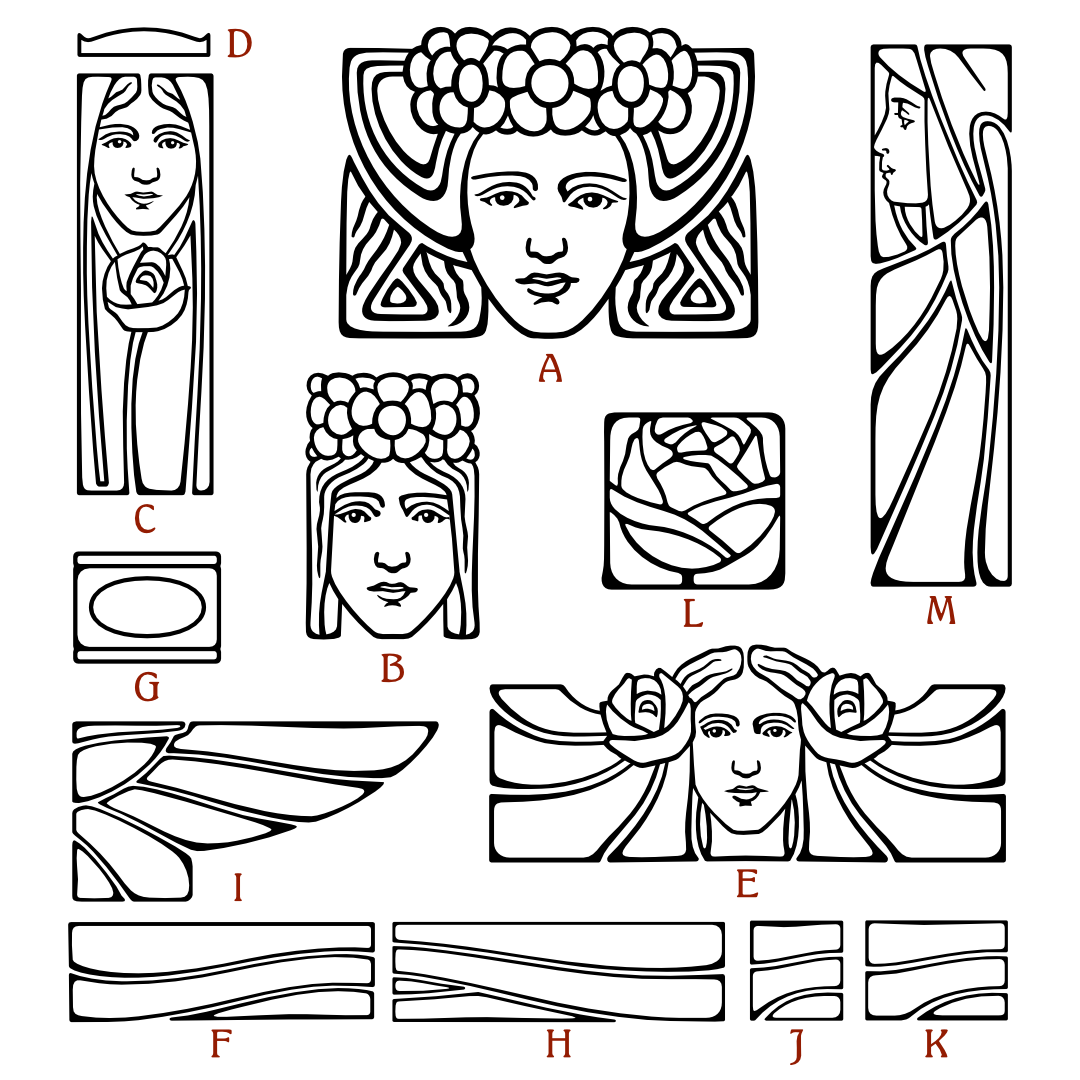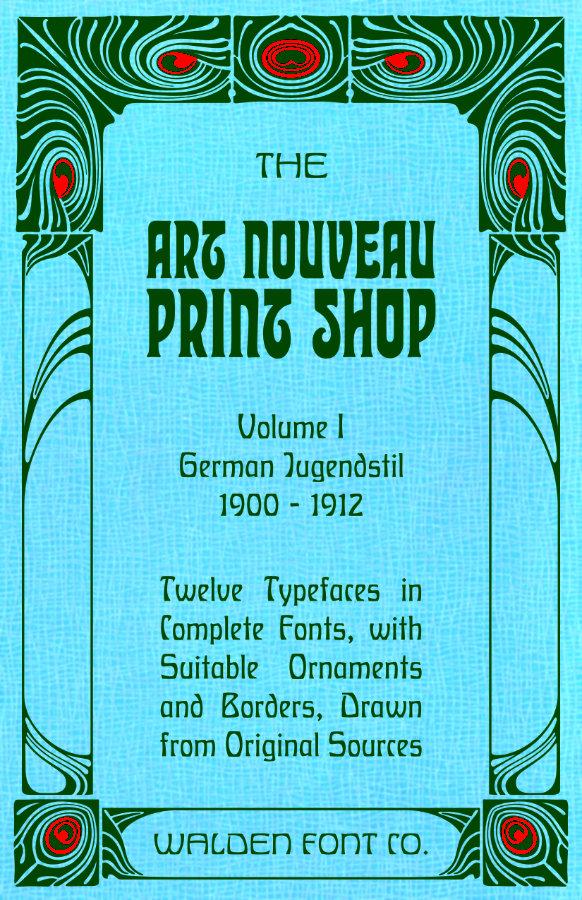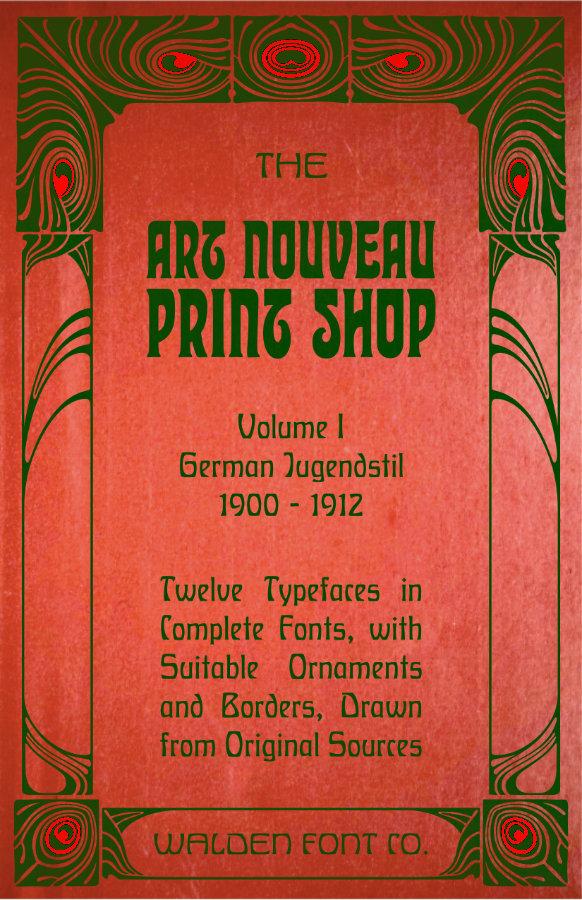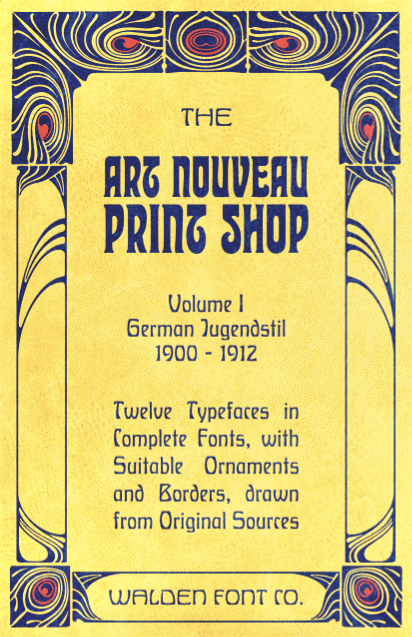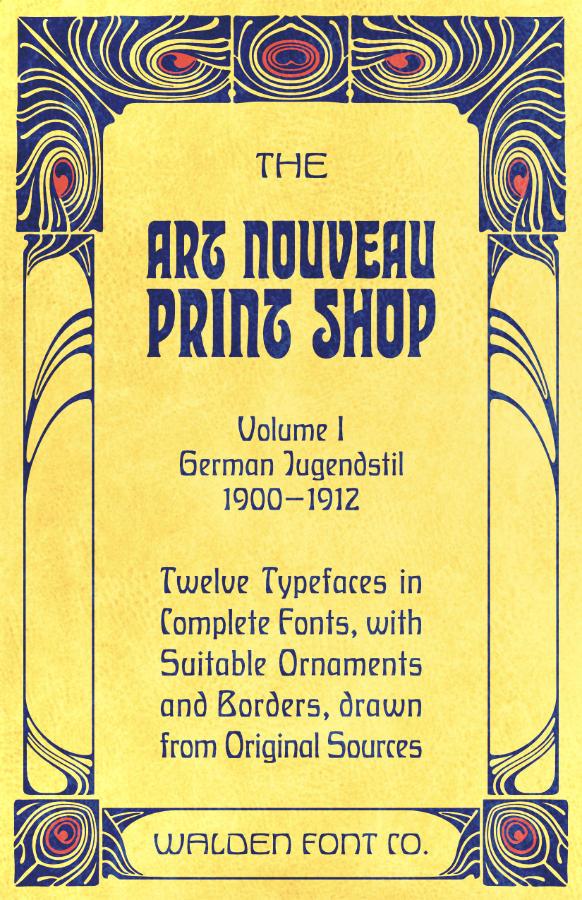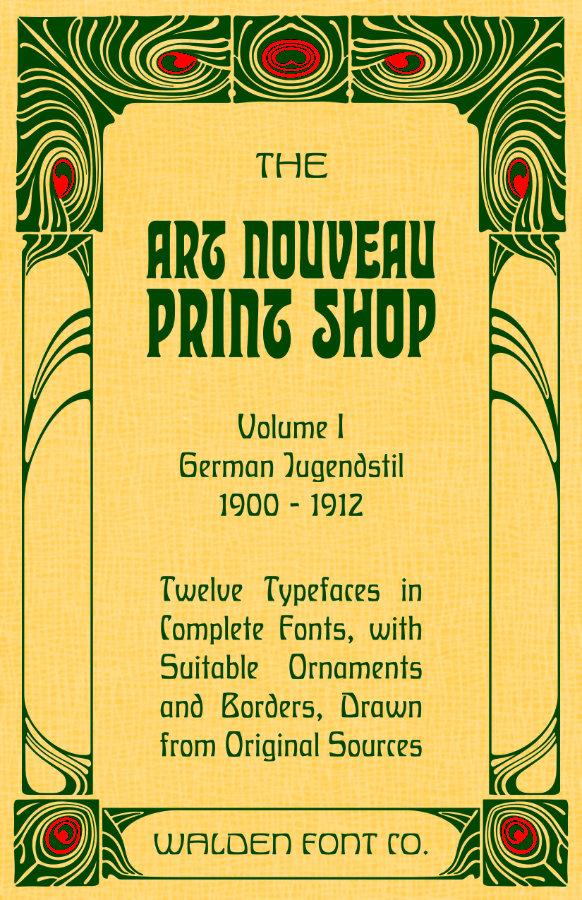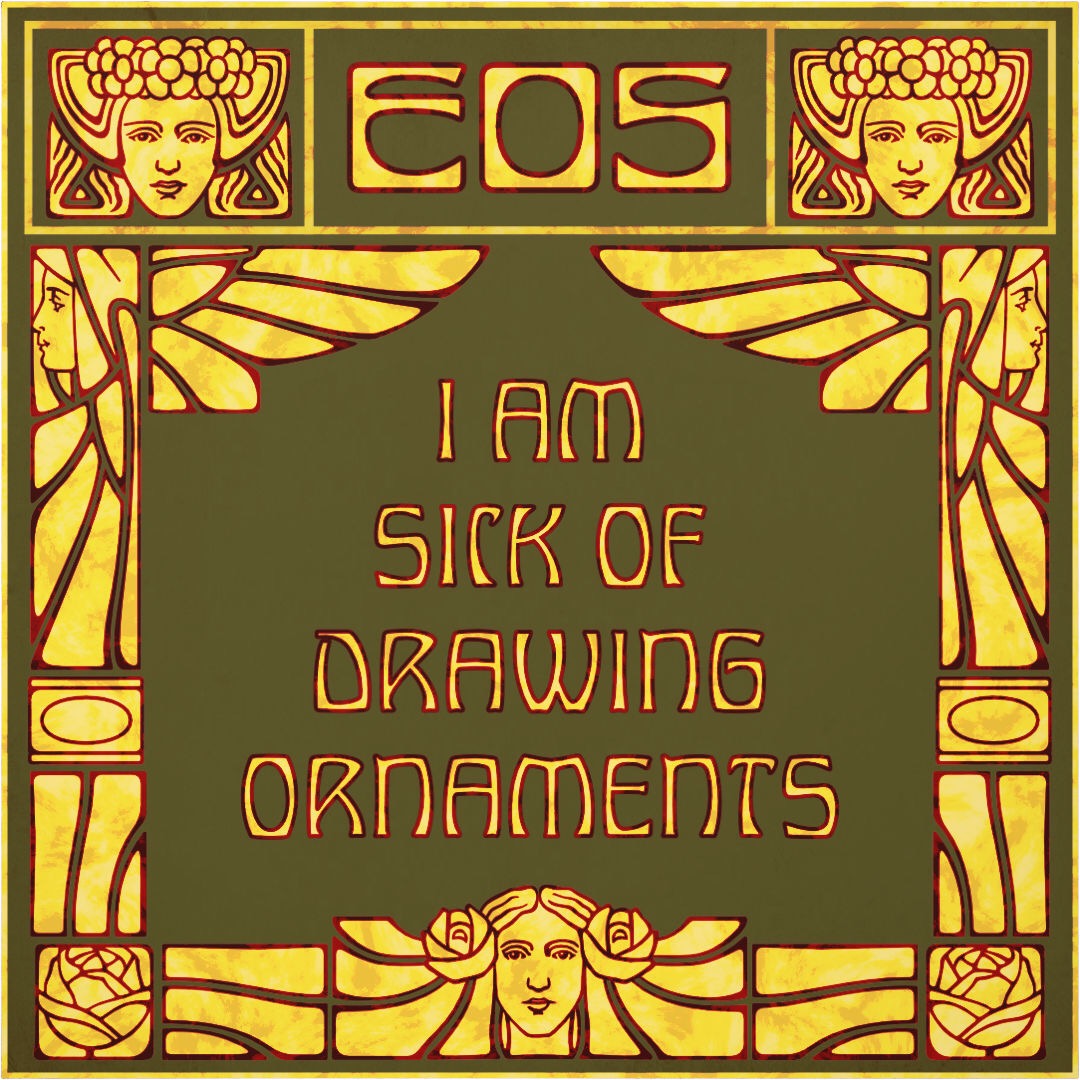
Jugendstil, Bordüren & Zierat
Gestern Abend war es schon spät, und zu mehr als einen Witz zu machen hatte ich keine Energie. In der Tat war das Bild ein erster Versuch an einem Titelblatt. Das brauche ich für meinen Website, aber auch, weil ich zu jedem Design Kit ein kleines Büchlein gestalte, in dem die Schriften erklärt werden, und das Anweisungen zu etwaigen OpenType features enthält, sowie verschiedene Anwendungen der Schriften.
Leider zeigt sich da oft, daß ich weder Künstler noch Grafischer Gestalter bin. Fehlschläge gehen mir viel leichter von der Hand als Erfolge...
Das angestrebte Titelblatt muß die folgenden Bedingungen erfüllen:
1. Sinn und Zweck müssen klar erkennbar sein, es muß also Art Nouveau/Jugendstil auf einen Blick vermitteln. (Das es sich um Schriften handelt, ist durch den Zusammenhang mit meiner Website gegeben)
2. Es verwendet nur Elemente aus dem Design Kit
3. Es muß grafisch ansprechend sein, und das Auge anziehen.
Mein erster Versuch erfüllt meiner Meinung nach vielleicht Punkt 1. und 2., aber keinesfalls 3. Zu fad, zu öd, auf Distanz nicht lesbar.
Hier habe ich mal mit verschiedenen Hintergründen gespielt:
Von den Farben her finde ich das unterste am ansprechendsten, wenn ich auch das Rot etwas kräftig finde. Aber das Gelb-Grüne sieht schon so schön alt aus 🙂
Allgemein verbinde ich irgendwie mit Jugendstil immer etwas, nun ja, plüschiges (vielleicht ist verspielt besser, jedenfalls für mein Gefühl jede Menge überflüssiges Gedönse), leicht "verdrecktes" (abgegriffen, staubig).
Das trifft vielleicht mehr auf den vorhergehenden Stil zu, der bei uns "Victorian", in Deutschland (glaube ich) "Wilhelminisch" bezeichnet wird. Der Jugendstil in seiner reinen Form (der damals ja nur "Modern" genannt wurde) will ja alles auf organische, aber klare Linien reduzieren. Von ~1896 bis 1913 sieht man da einen dramatischen Gedönsschwund. Ich will hier etwa die Mitte treffen, daher nur die Pfauenbordüre.
Eine Alternative wäre eine dünne Umrandung (die Edellinien von weiter oben), und eine markantes Gesicht. Unser Auge wird ja von Gesichtern angezogen.
Vielleicht diese Dame?
Nackedeis jeden Geschlechts waren ja auch äußerst beliebt. Das kann ich aber hier nicht bringen, sonst haut mir Google eine auf den Deckel.
Da bemerke ich gerade ein ganz anderes Problem. Und zwar passen hier Titel und Untertitel zueinander.  Aber das nächste Set wird französische Schriften enthalten, und das hieße dann "Art Nouveau Print Shop Volume II French Art Nouveau".  So'n Blödsinn.
Ich kann das "Art Nouveau" schlecht aus dem Titel nehmen. Eventuell muß ich mich mit einer der weniger bekannten französischen Bezeichnungen behelfen, z. b. Style Nouille, L'Art Moderne, oder Style Métro. Naja, das wird ja noch ein Weilchen dauern bis ich an diese Brücke komme.
Entschuldigung, an dem Titel macht den Schriftsetzer und Korrektor das Divis zwischen den Jahreszahlen nervös. Ich kann gar nicht drüber wegsehen.
Unten im Block bestimmt die letzte Zeile die zu weiten Wortzwischenräume darüber. Deshalb würde ich die bearbeiten. Im Bleisatz ginge das nicht, aber digital kann man die unsichtbar kleiner machen und schmaler zerren, um die zu großen Wortzwischenräume darüber zu verbessern. In Kleinformaten kann man über so etwas gut hingwesehen, auf Titeln in großen Schriften wirkt es etwas unbeholfen. Früher wurde an solchen Schriftmustern solange herumformuliert, bis ein Blocksatz wie von selbst gut gesessen hat.
Auweh. Danke für den Hinweis, Martin. Besser so, oder?
Für Papier und Farbigkeit assoziiere ich mit dem Jugendstil gerne das "look and feel" einer Farblithografie, also leicht "verwaschene" Farben, körnige Flächen und ein sichtbares Papiersieb. Die Farbigkeit des letzten Entwurfs finde ich da schon passend, aber das Papier wäre mir noch zu elefantenhautartig. Also etwa so:
Das ist doch noch keine Fieselei. Das sind alles noch ganz handliche Bleiklötzchen, die man da in der Hand hat. 😉
Spannend wird der Versalausgleich bei einer 4/6 Punkt Schrift (4 Punkt Schriftbild auf 6 Punkt Kegel gegossen).
Ich habe für sowas u. a. 1/4 Punkt Neusilberspatien.
Sowas macht man nicht jeden Tag. Aber wenn, dann ist es jedesmal wieder eine Herausforderung an die ruhige Hand und die trüben Augen!
Nur so zur Erinnerung: 1 Didot Punkt entspricht 0,376 mm.